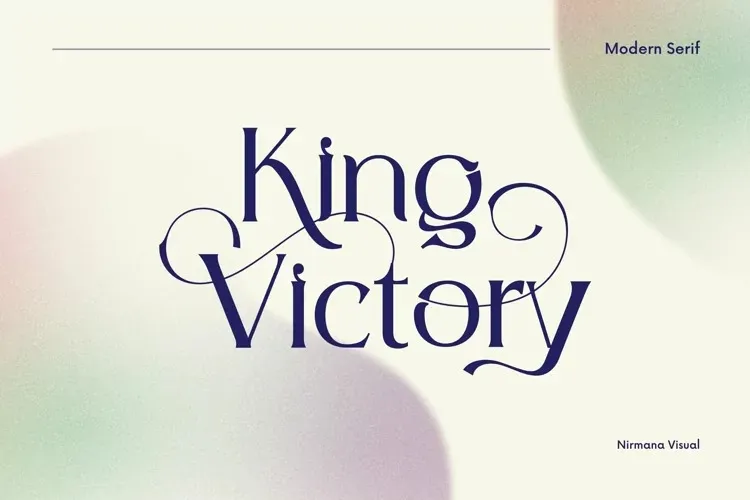
A fonte ‘King Victory’ traz uma sensação única no mundo das fuentes serif, com seus surpreendentes desenhos retorcidos que se assemelham a travessões presas entre si e um toque de ornamentação delicada e elegante. Esta escolha de fontes é perfeitamente adaptável para aplicações relacionadas à moda ou design editorial, enquanto mantém o equilíbrio perfeito entre caráter masculino e feminino. Seja ela a estrela em uma campanha de marketing fashionista, ou um toque refinado em um layout editorial, esta font é um elemento chave para qualquer designer que busca criatividade sem comprometer a elegância da tipografia serif.